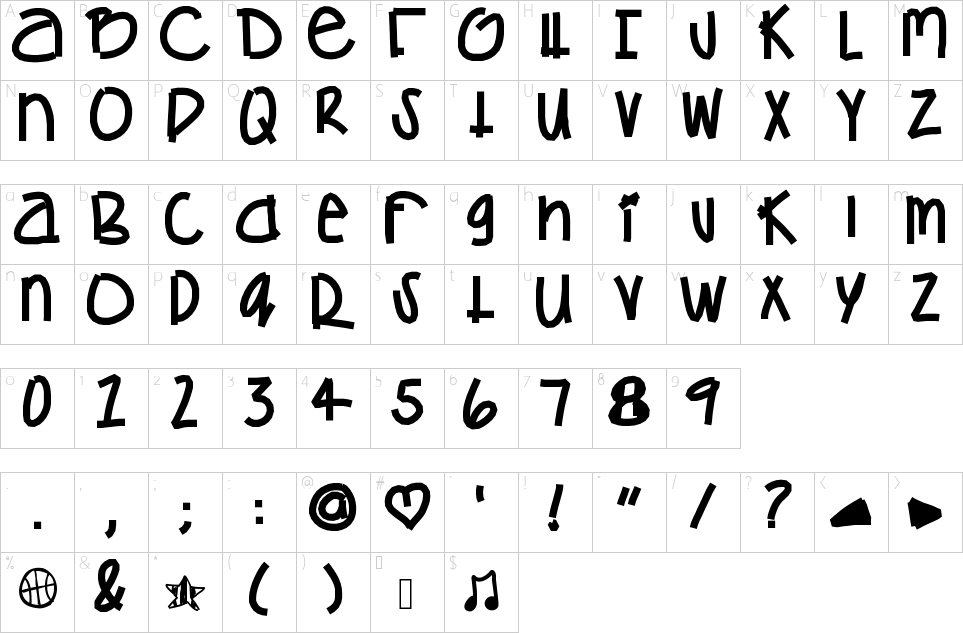
Aqui está uma descrição para a página de download da fonte ‘Games Getchu Nowhere Font’, no estilo solicitado: O Games Getchu Nowhere é uma fonte única e minimalista, ideal para os entusiastas de jogos que procuram uma aparência distinta em suas criações digitais. Desenvolvida pelo designer desconhecido Des Gomez, essa font foi projetada para adicionar um toque especial a qualquer projeto visual. Com 3.307 downloads na plataforma, é claro que a Games Getchu Nowhere está se destacando no mundo do design digital. Sua simplicidade e modernidade tornam-a uma escolha atraente para designers de jogos ou aqueles buscando algo diferente do básico em suas aplicações digitais. Seja para títulos, texturas, ou qualquer outro elemento visual que você pode imaginar, essa font será um diferencial positivo para seu design. Adquira sua própria cópia e experimente o poder de expressão visual dessa font única hoje mesmo. Sua criação digital será a prova viva da sua criatividade!